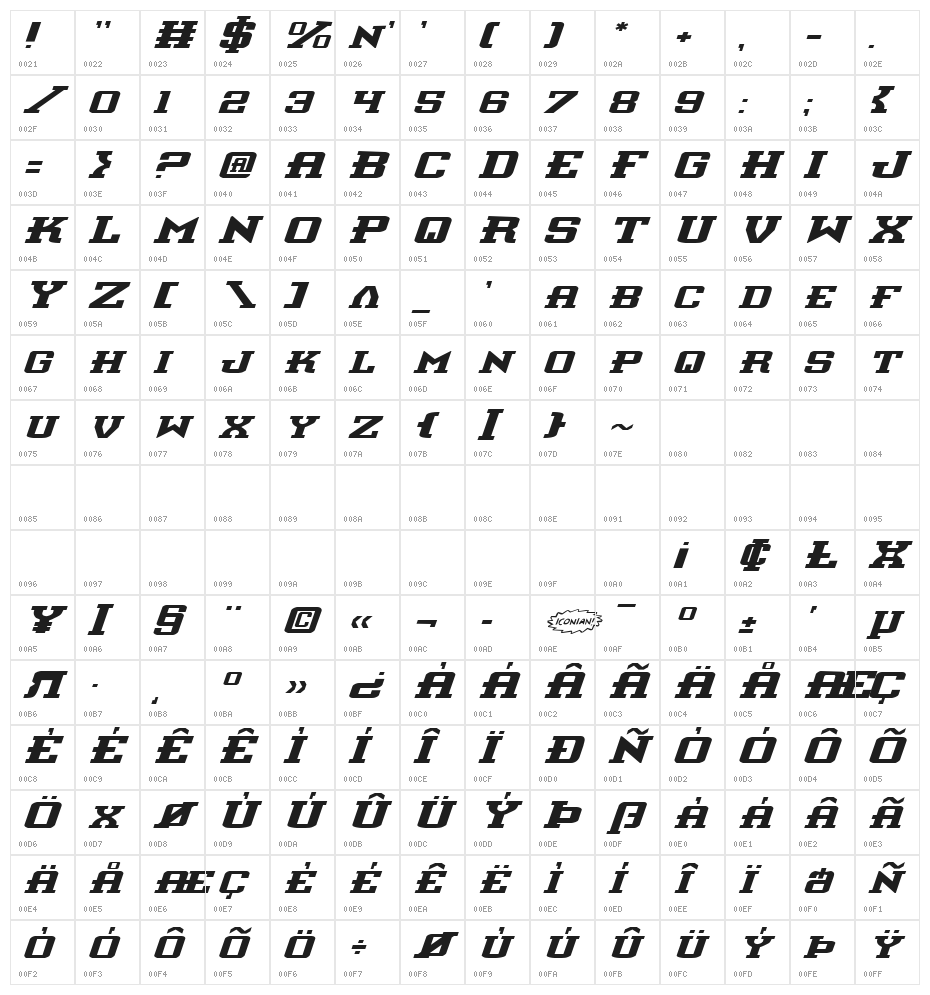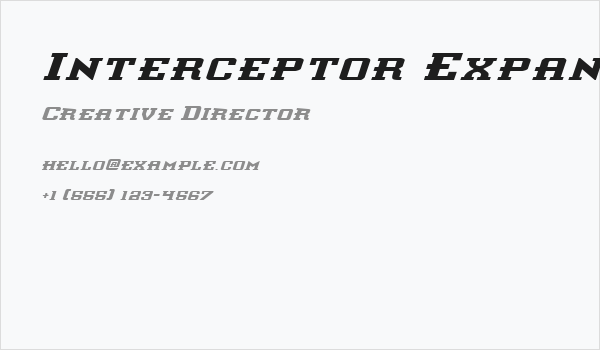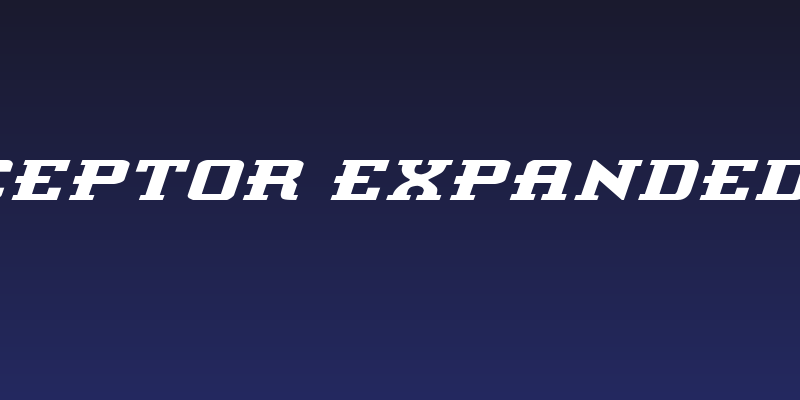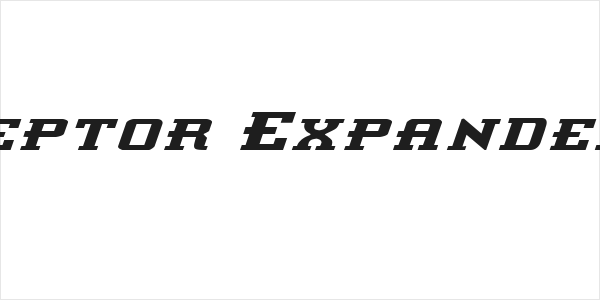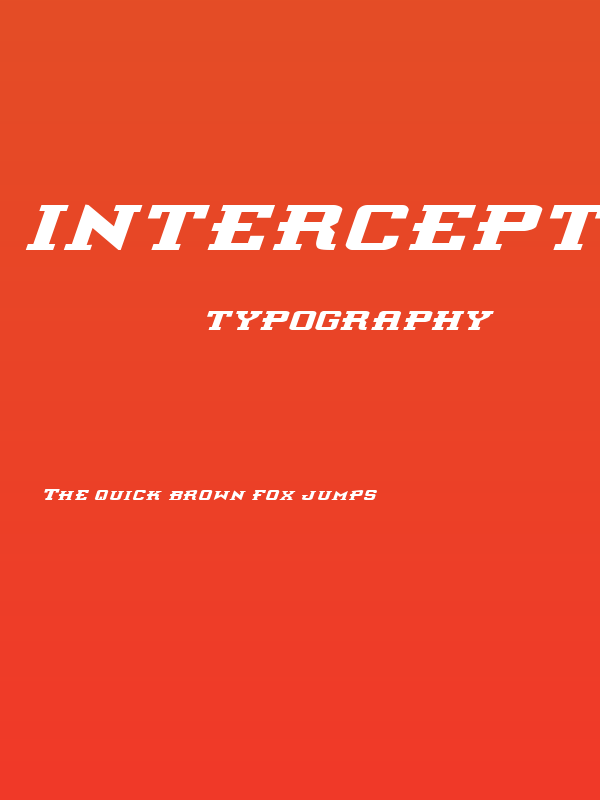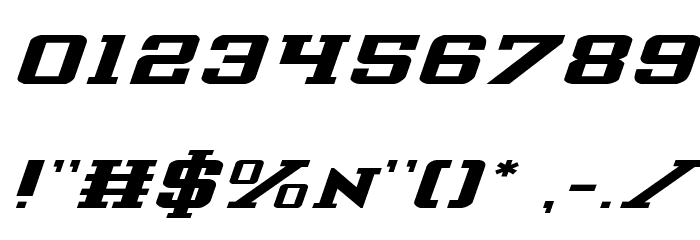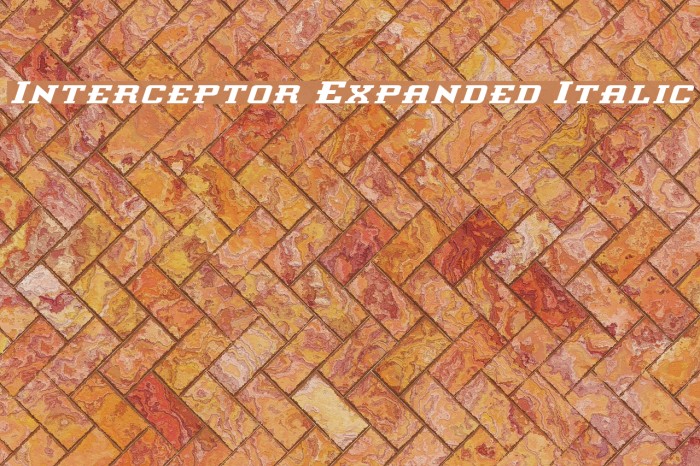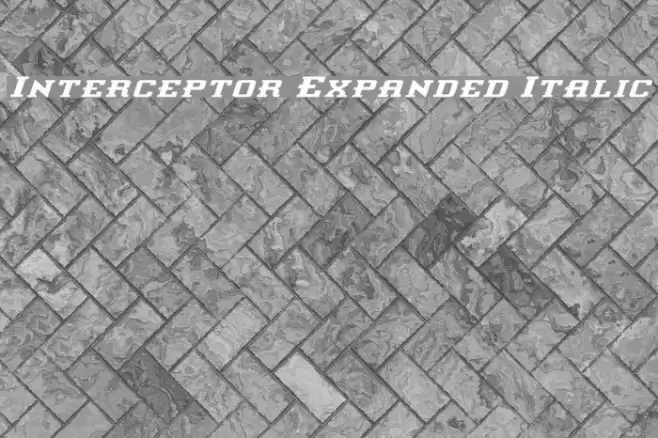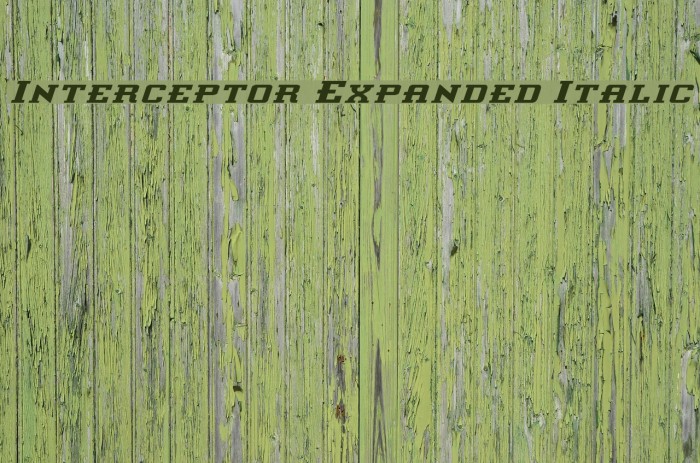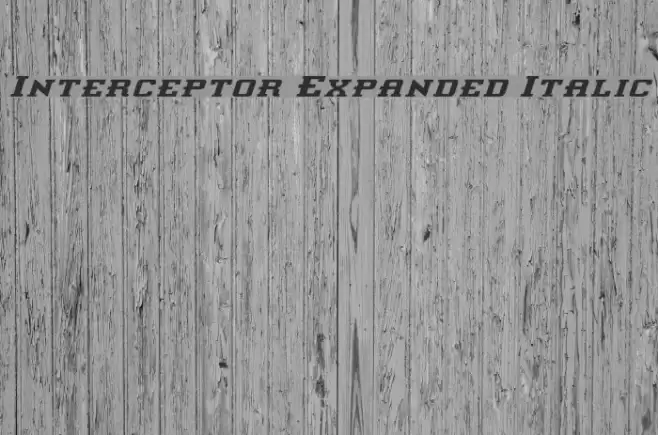
Interceptor Expanded Italic Font
| Vorgeschlagene Projekte | Ideal for sports branding, automotive designs, dynamic posters, and headlines that require a strong visual impact. |